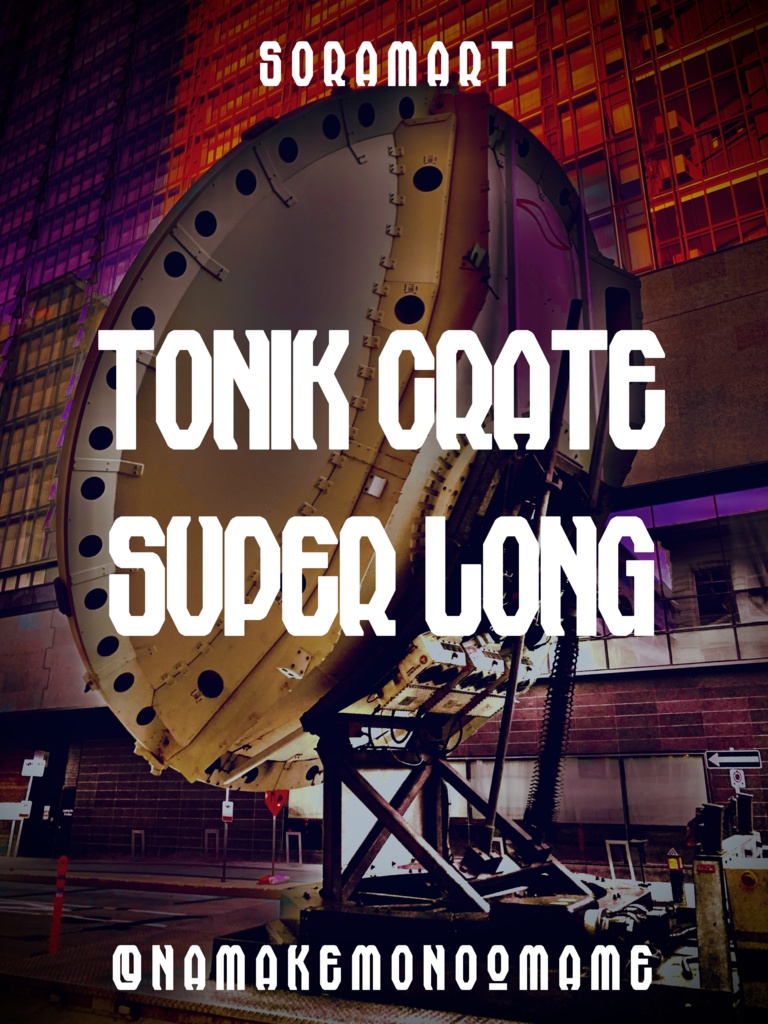
そらマートフォントデータ”Tonik Crate Super Long”ダウンロード商品¥ 2,500カートに入れるギフトとして贈る「ギフトとして贈る」とはちょっと近未来感のあるポップ調縦長フォント "Tonik Crate Super Long" です。 「TrueTypeフォントファイル」という形式です。 ダウンロードした後、Zipファイル内のデータをインストールしてお使いください。 このフォントは商用利用可となっております。 お客様の制作・創作活動のお役に立てれば幸いです。 ※使用上の注意事項などは、添付のReadmeをお読みください。そらマートFANBOX開設中フォント・書体フォントデータ”Hazy Flap”そらマート¥ 0フォント・書体フォントデータ”Amber Nouveau Tight”そらマート¥ 2,500フォント・書体フォントデータ”Amber Nouveau Wide”そらマート¥ 2,500フォント・書体フォントデータ”Amber Nouveau”そらマート¥ 2,500フォント・書体フォントデータ”RANMMA Drive”そらマート¥ 2,500フォント・書体フォントデータ”Dandy Laser Max”そらマート¥ 2,500フォント・書体フォントデータ”Dandy Laser”そらマート¥ 2,500フォント・書体フォントデータ”Bubblegum Beat”そらマート¥ 2,500フォント・書体フォントデータ”Caltrop Serif LLL”そらマート¥ 2,500フォント・書体フォントデータ”Caltrop Serif LL”そらマート¥ 2,500フォント・書体フォントデータ”Caltrop Serif”そらマート¥ 2,500フォント・書体フォントデータ”Dot Eat Bug Acid”そらマート¥ 2,500フォント・書体フォントデータ”Dot Eat Bug Mild”そらマート¥ 2,500フォント・書体フォントデータ”Dot Eat Bug”そらマート¥ 2,500フォント・書体フォントデータ”Solid Voltage Strike”そらマート¥ 2,500フォント・書体フォントデータ”Solid Voltage”そらマート¥ 2,500フォント・書体フォントデータ”Henge Edge Rock”そらマート¥ 2,500フォント・書体フォントデータ”Henge Edge Tall”そらマート¥ 0フォント・書体フォントデータ”Henge Edge”そらマート¥ 0フォント・書体フォントデータ”Chisel Stroke Wide”そらマート¥ 2,500もっと見る